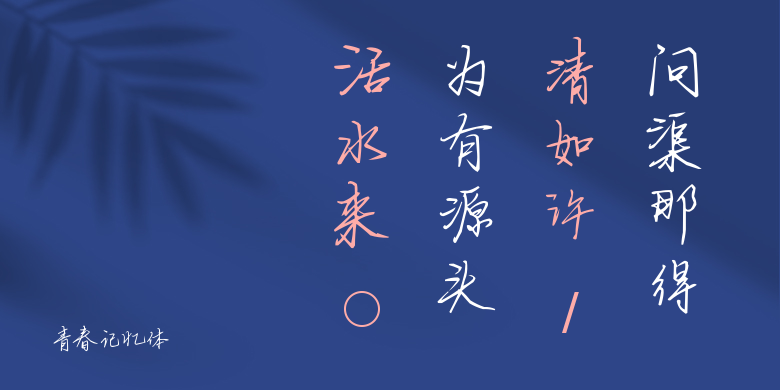
青春记忆体
青春记忆体,这款字体结构工整、笔画清晰,兼顾美观与易读性,适用于标题、正文、海报、包装、LOGO 等多种场景。字形优雅稳定,风格百搭耐看,适配日常排版与创意设计,让文字呈现更舒适、更具质感。青春记忆体一笔一画,皆是细节,以均衡的比例、流畅的线条打造舒适视觉体验,字形端正大气,风格简约现代。无论是商业设计、品牌宣传还是日常排版,都能轻松驾驭,让文字更有格调与力量。青春记忆体字体下载。